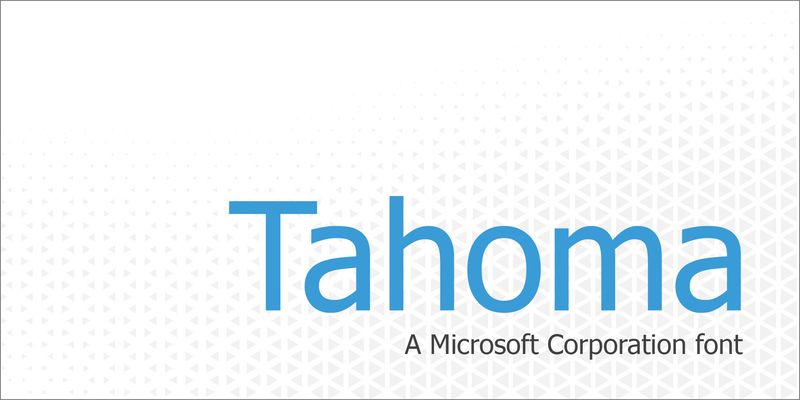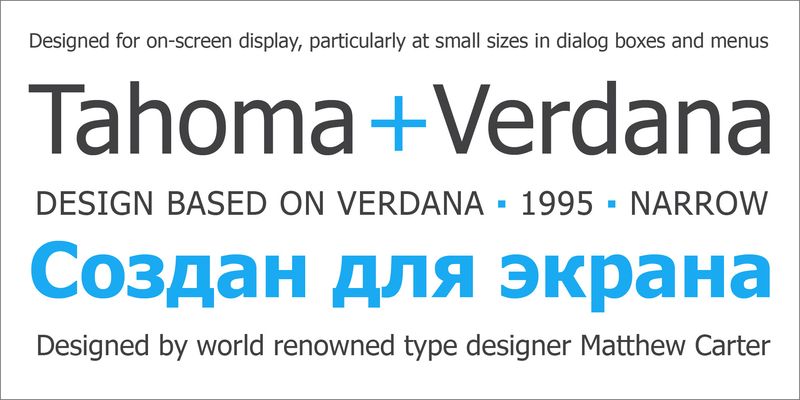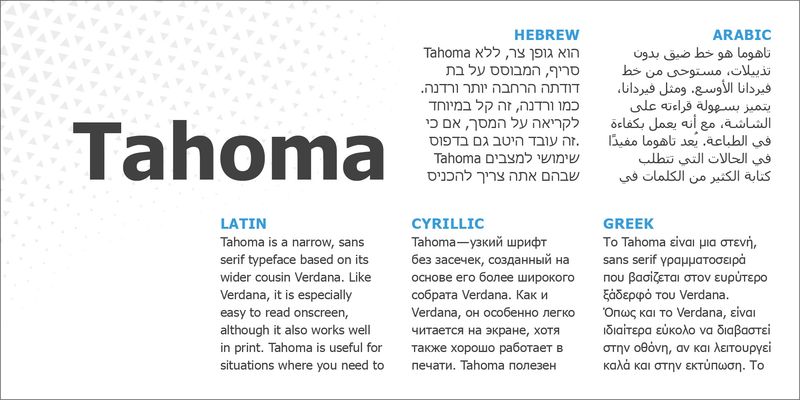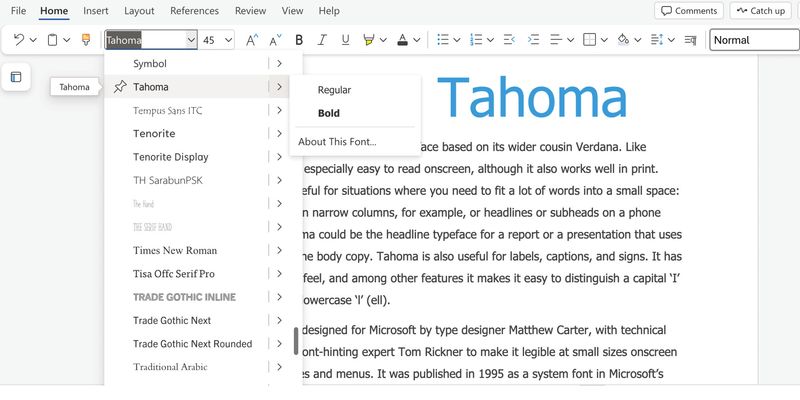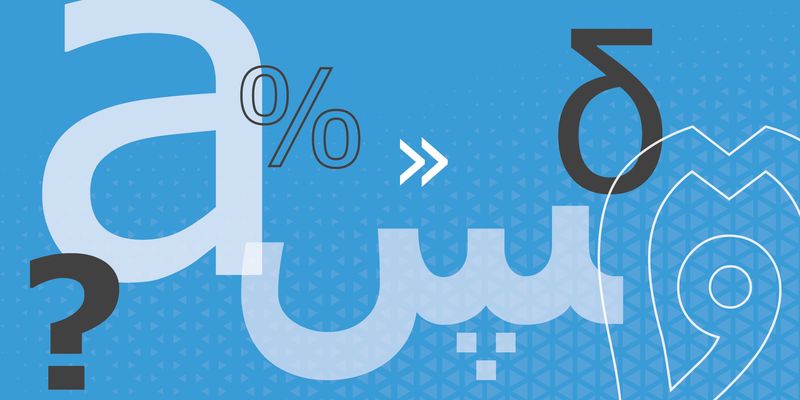
Tahoma est une police étroite sans empattement, inspirée de sa cousine plus large Verdana. Comme Verdana, elle est particulièrement lisible à l’écran, mais fonctionne également bien sur papier. Tahoma est utile pour les situations où il faut insérer beaucoup de mots dans un espace restreint : une newsletter en colonnes étroites, par exemple, ou des titres et sous-titres sur un écran de téléphone. Tahoma pourrait être la police de titre d’un rapport ou d’une présentation utilisant Verdana pour le corps du texte. Tahoma est également utile pour les étiquettes, les légendes et la signalétique. Elle offre une impression claire et ouverte, et permet, entre autres, de distinguer facilement un « I » majuscule (i) d’un « l » minuscule (el).
Tahoma a été conçue pour Microsoft par le créateur de polices Matthew Carter, avec des ajustements techniques de Tom Rickner, expert en optimisation de polices, afin de la rendre lisible en petites tailles à l’écran, dans les boîtes de dialogue et les menus. Elle a été publiée en 1995 en tant que police système dans le système d’exploitation Windows 95 de Microsoft.
Tahoma a deux épaisseurs clairement distinguées, Regular et Bold, mais pas de styles italiques.